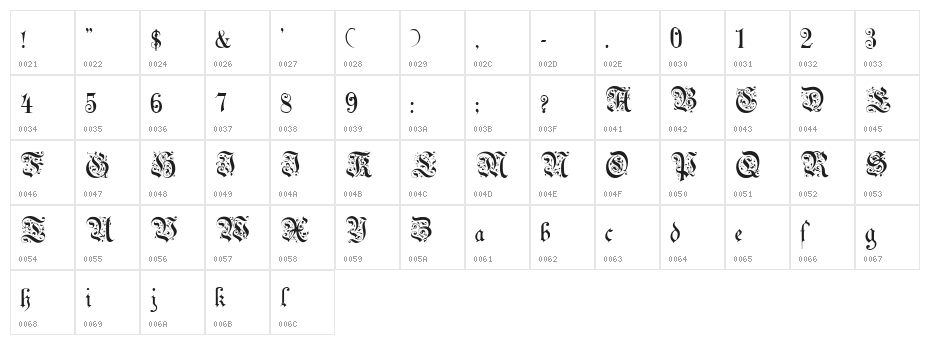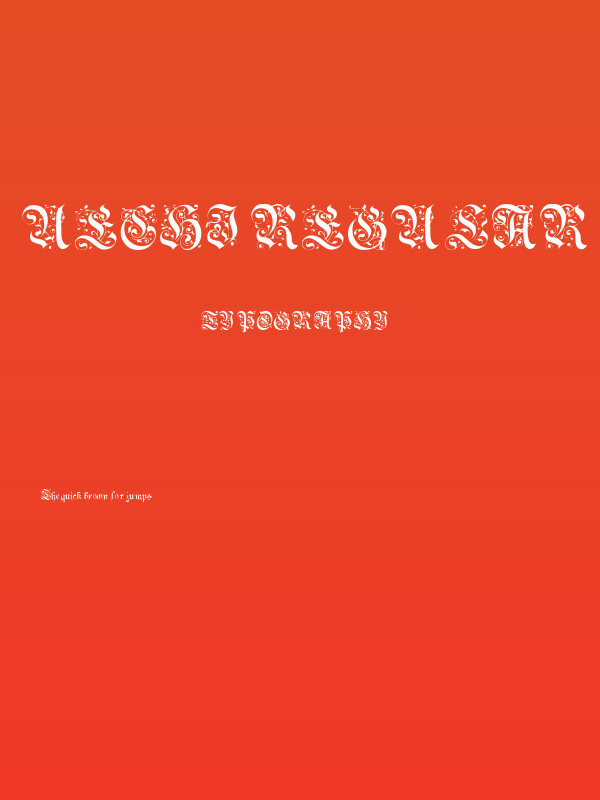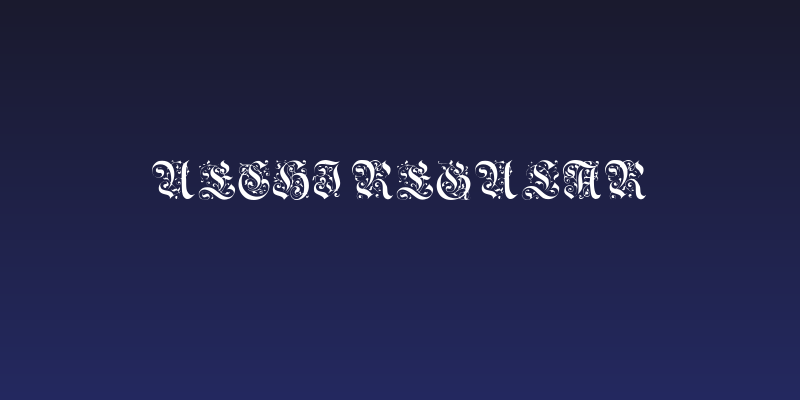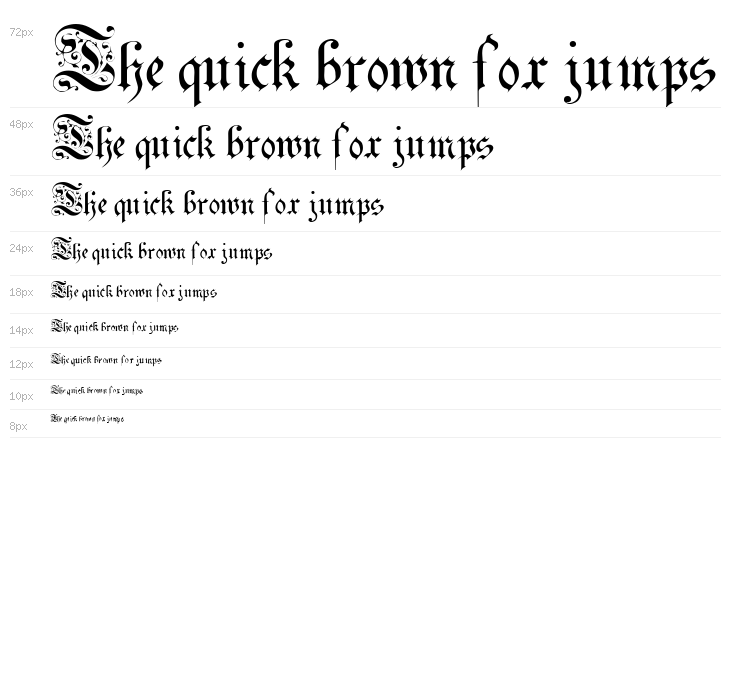
Uechi Regular Font
✎ Gothic
| Caso de uso | Logos, Headlines, Decorative text |
| Proyectos propuestos | Suitable for wedding invitations, gothic-themed posters, historical documents, and decorative book covers. |